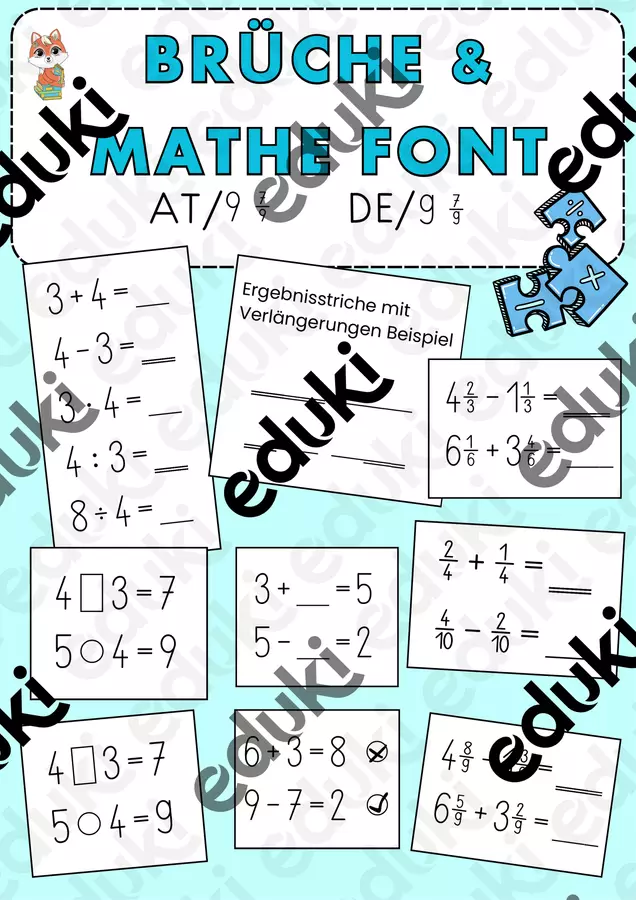
Die Brüche gehen bis 10/10. Die wichtigsten Rechenzeichen für die Grundschule sind dabei.
Die Zahlen und Brüche habe ich so formatiert, dass man gänzlich ohne Leertaste auskommt. Sie haben, bis auf die 1, alle die gleichen Abstände.
Zusätzlich habe ich Ergebnisstriche in 2 Versionen hinzugefügt. Einfach und doppelt. So hat das lästige Rumschieben der Linien bei Canva endlich ein Ende. Die einzelnen Striche kann man auch wunderbar in der Mitte einer Rechnung einsetzen, damit Kinder die Zahlen einfügen können.
Ebenso gibt es Verlängerungsstriche, die bündig an die Ergebnisstriche anschließen. Somit perfekt für längere Ergebnisse.
Des weiteren ist ein Kreis dabei. Diesen kann man einsetzen, um die Kinder die Rechenzeichen ausfüllen zu lassen. Oder man benutzt ihn als "Richtig oder Falsch" am Ende einer Rechnung.
Auch ein Rechteck gibt es. In dieses kann man die Kinder einstellige Zahlen oder auch Rechenzeichen schreiben lassen.
Den Brüche und Mathe-Font gibt es für DE und AT. Die 9 ist unterschiedlich. Wer noch eine andere 7 (ohne Strich) benötigt, bitte einfach Bescheid geben. Ich kann gerne noch eine weitere Schrift hochladen.
Mit dieser Schrift habt ihr eine merkliche Zeiteinsparung bei der Erstellung von Mathe-Arbeitsblättern, da lästiges formatieren und zig mal Leertaste drücken wegfällt.